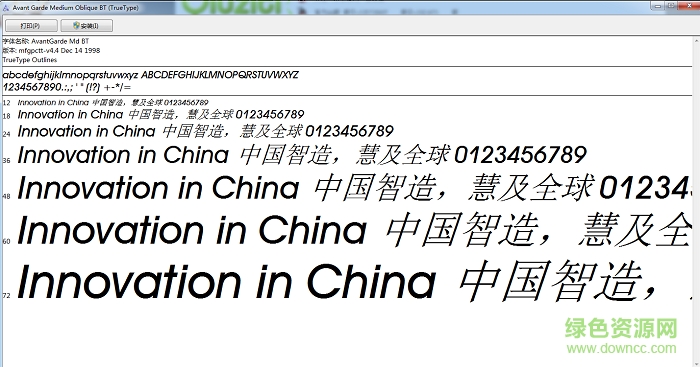
avantgarde md bt 普通 西方常規(guī)體
avantgarde md bt字體是一款無(wú)襯線裝飾的常規(guī)普通西方字體,字形簡(jiǎn)約,簡(jiǎn)潔爽朗,閱讀效果良好,可以用于報(bào)刊正文、雜志、平面設(shè)計(jì)等方面,需要的朋友快來(lái)下載吧!